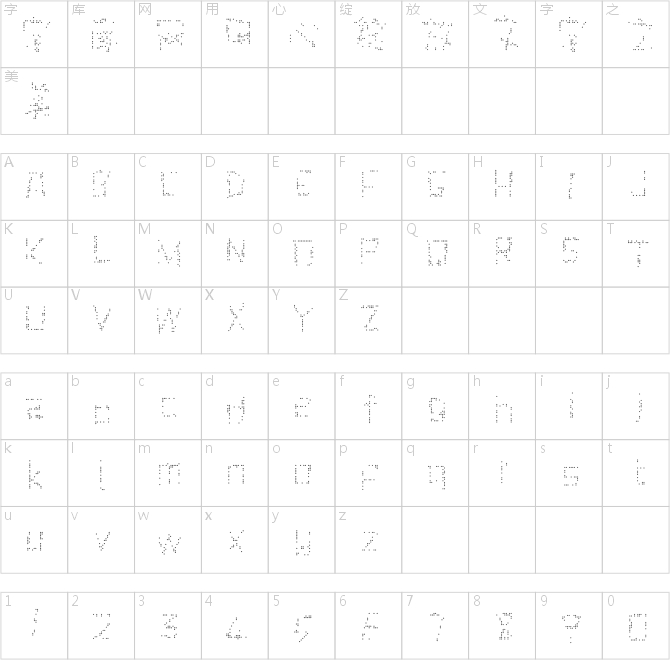
字玩智能字浪 55 詳情頁
字體名稱: 字玩智能字浪
字玩智能字浪 55
字玩智能字浪 55字體字庫是一款讓人賞心悅目、百看不厭的中文字體,適合各類廣告和產(chǎn)品包裝設(shè)計應(yīng)用,字體大小13.07MB,格式為otf字體,上傳用戶是1733150348,作者/版權(quán)方為銳字潮牌